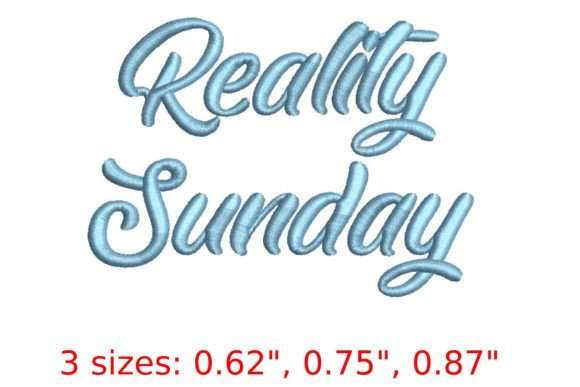
Reality Sunday Embroidery Font
Nếu bạn đang tìm kiếm các tài nguyên chất lượng cao như Reality Sunday Embroidery Font, gói cao cấp này là một lựa chọn tuyệt vời cho các dự án sáng tạo của bạn.
Được chế tác với độ chính xác cao, Reality Sunday Embroidery Font cung cấp các vector sạch, kiểu chữ mượt mà và giấy phép thương mại để bạn yên tâm.